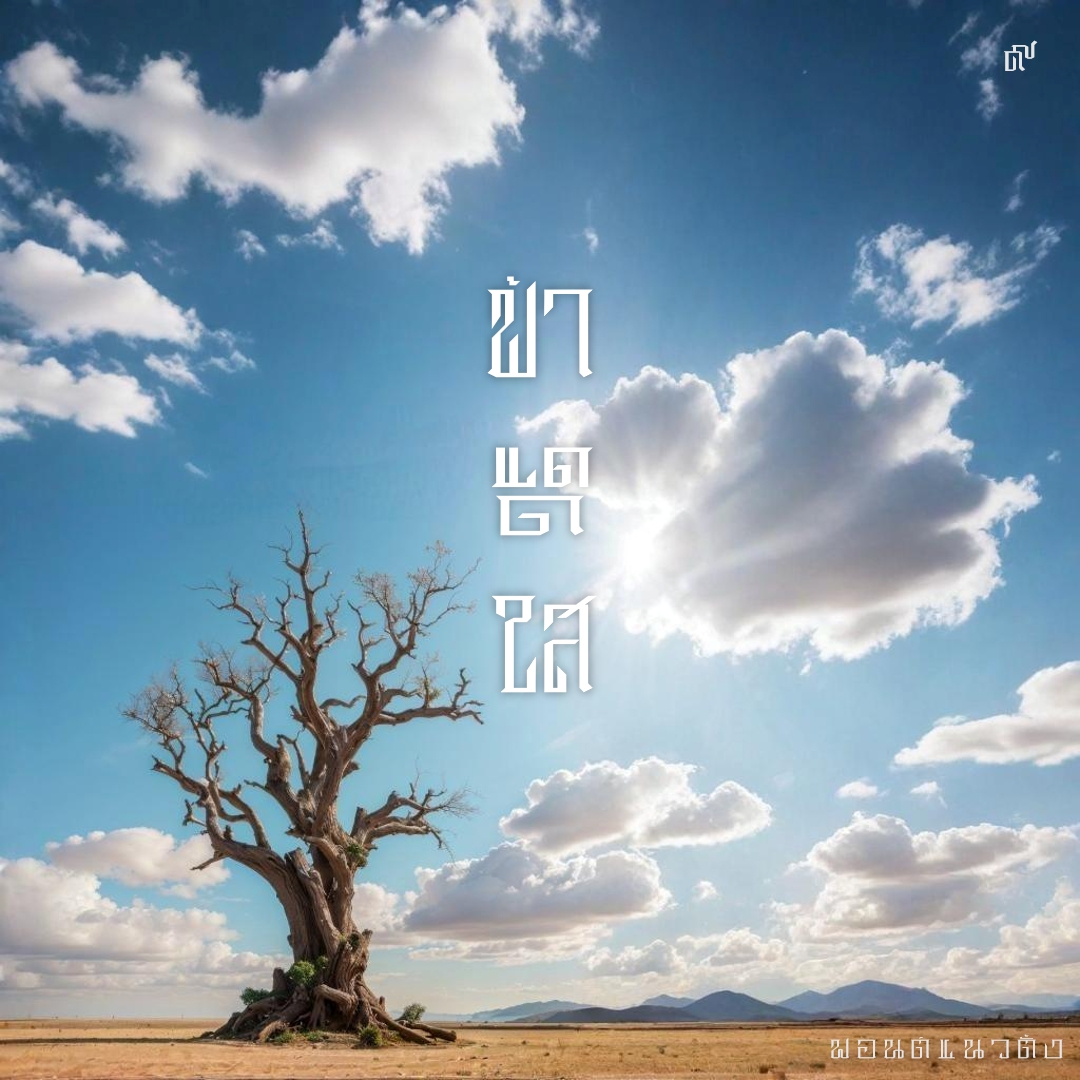
ฟอนต์ แนวตั้ง
ฟอนต์แนวตั้ง แนวคิดจาก CJK fonts ที่สามารถเขียนและอ่านตามแนวตั้งได้ แต่ต้องพิมพ์เป็นคำๆ แบ่งด้วยช่องว่าง(space) ฟอนต์จะจัดอักษรให้เป็นกลุ่มๆให้ไม่กว้างเกินไป (พยัญชนะไม่เกิน 5 ตัว)
ชื่อฟอนต์ : แนวตั้ง
ฟอนต์แนวตั้ง แนวคิดจาก CJK fonts ที่สามารถเขียนและอ่านตามแนวตั้งได้ แต่ต้องพิมพ์เป็นคำๆ แบ่งด้วยช่องว่าง(space) ฟอนต์จะจัดอักษรให้เป็นกลุ่มๆให้ไม่กว้างเกินไป (พยัญชนะไม่เกิน 5 ตัว)
เบื้องหลัง เล็กน้อย..มหาศาล
1. ออกแบบฟอนต์ 15 รูปแบบ ต่อ 1 ตัวอักษร
2. เพื่อไม่ต้องแยกเป็น 5 ฟอนต์แบบที่เคยทำ ต้องเขียนโปรแกรมมากกว่า 360 functions
2 พยัญชนะ = 9 functions (CC, CCv, CCvv, CvC, CvCv, CvCvv, CvvC, CvvCv, CvvCvv)
3 พยัญชนะ = 27 functions
4 พยัญชนะ = 81 functions
5 พยัญชนะ = 243 functions
นี่ถ้าไม่ใช้เทคนิคใหม่ ก็คงทำไม่ไหว (เพราะขนาดใช้แล้ว เจอ 6 พยัญชนะ จะต้องทำอีก 729 functions ..หมอบ)
ยิ่งตอนเจอ bug นี่ ถึงกับถอนหายใจ เฮือก